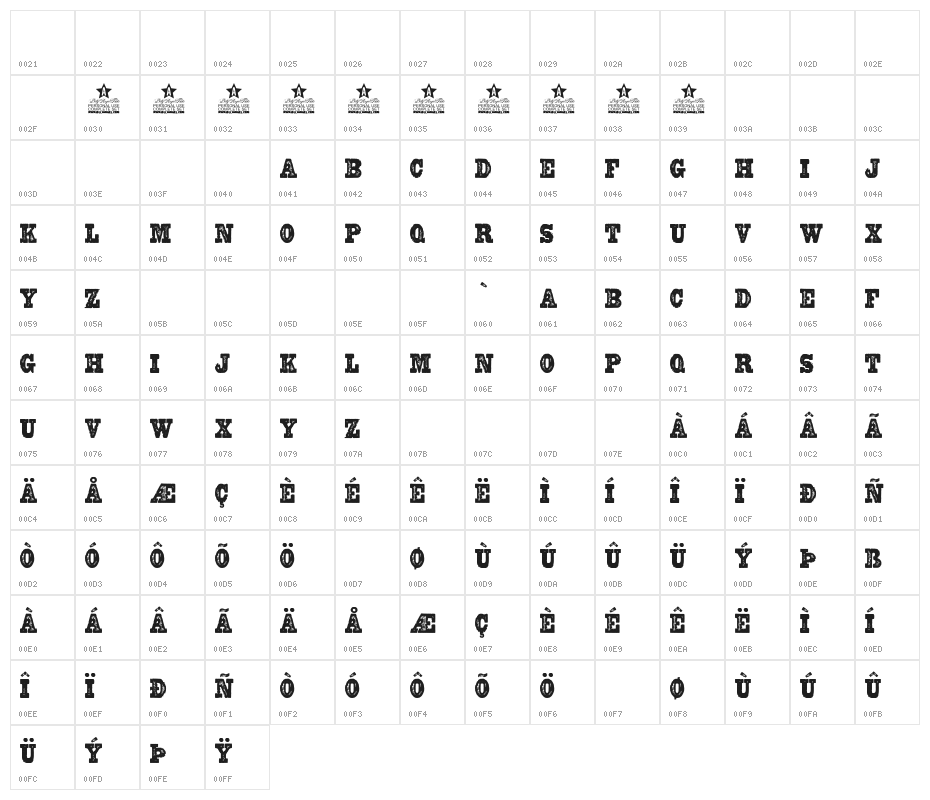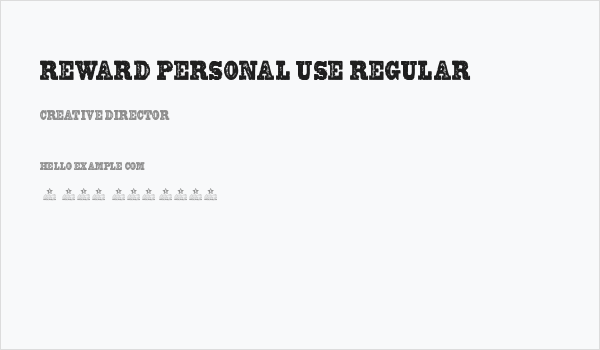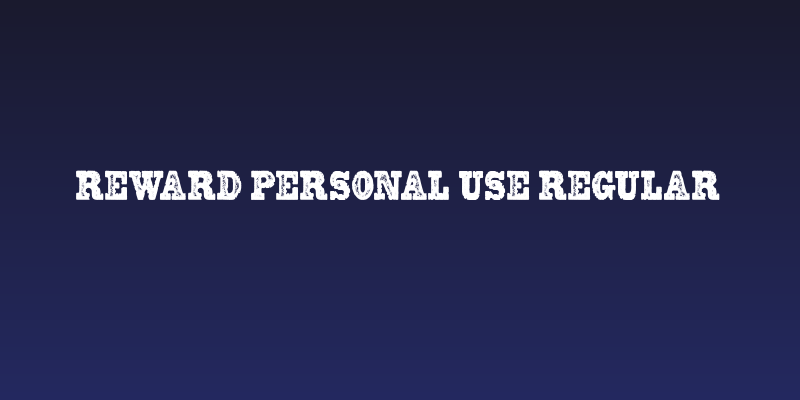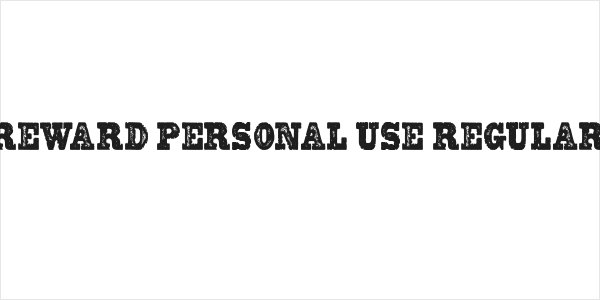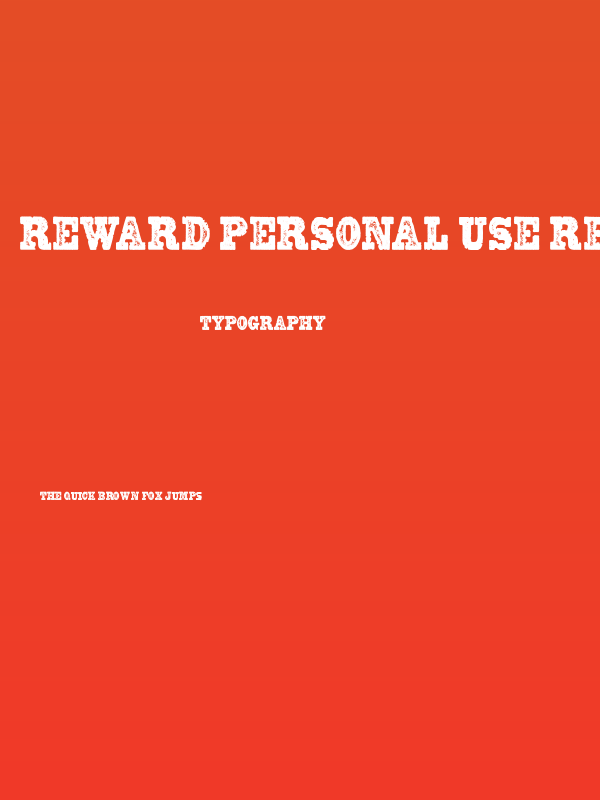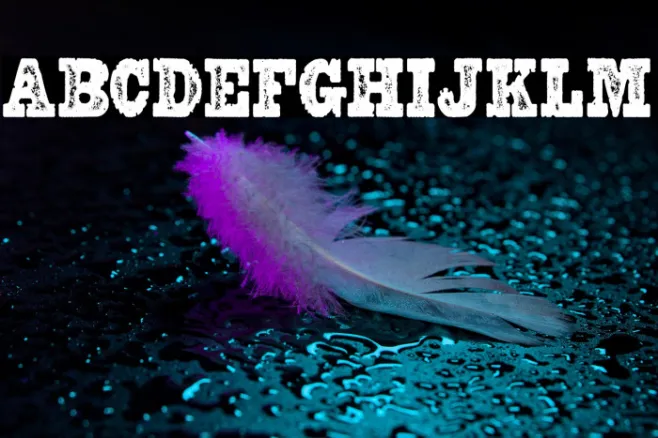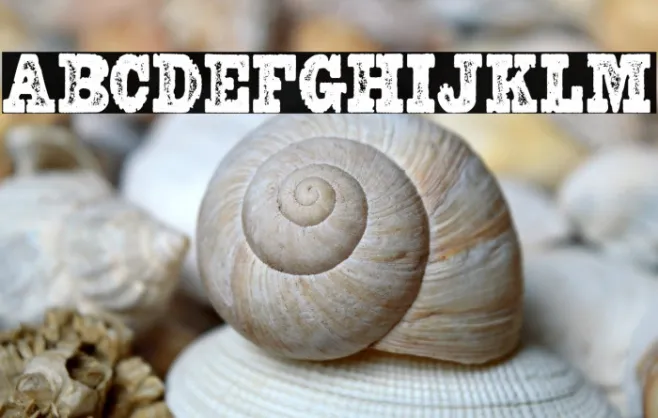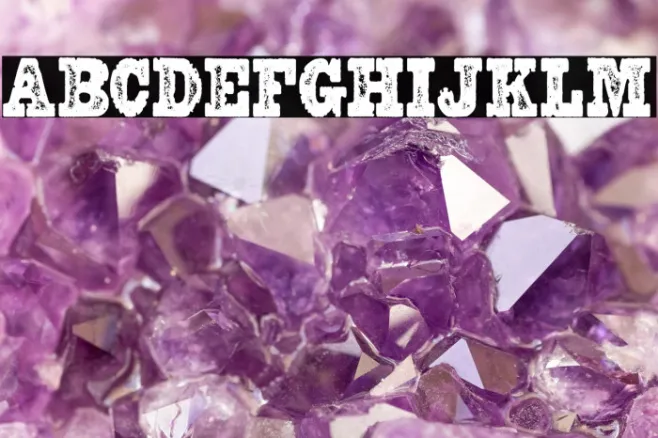
REWARD PERSONAL USE Regular Font
✎ Western
| Famille de police | REWARD PERSONAL USE |
| Catégories | Western |
| Projets proposés | Ideal for vintage-themed posters, branding, logos, and signage that require a strong, eye-catching presence. |